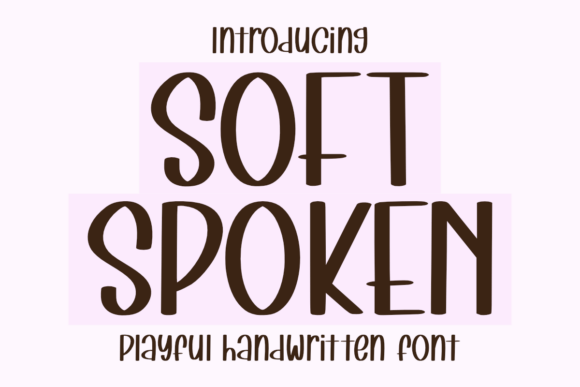
Soft Spoken
Soft Spoken – Une Typographie d’Exception
La police Soft Spoken séduit par son style manuscrit doux et arrondi, parfait pour apporter une touche de charme et de clarté à tout projet de design. Idéale pour le packaging, le branding lifestyle et les citations inspirantes, elle crée une ambiance accueillante qui capte immédiatement l’attention.
Caractéristiques Clés
- Trait manuscrit élégant aux courbes généreuses
- Formes allongées qui améliorent la lisibilité
- Cohérence stylistique adaptée aux supports numériques et imprimés
- Polyvalence: packaging, logos, affiches, citations inspirantes